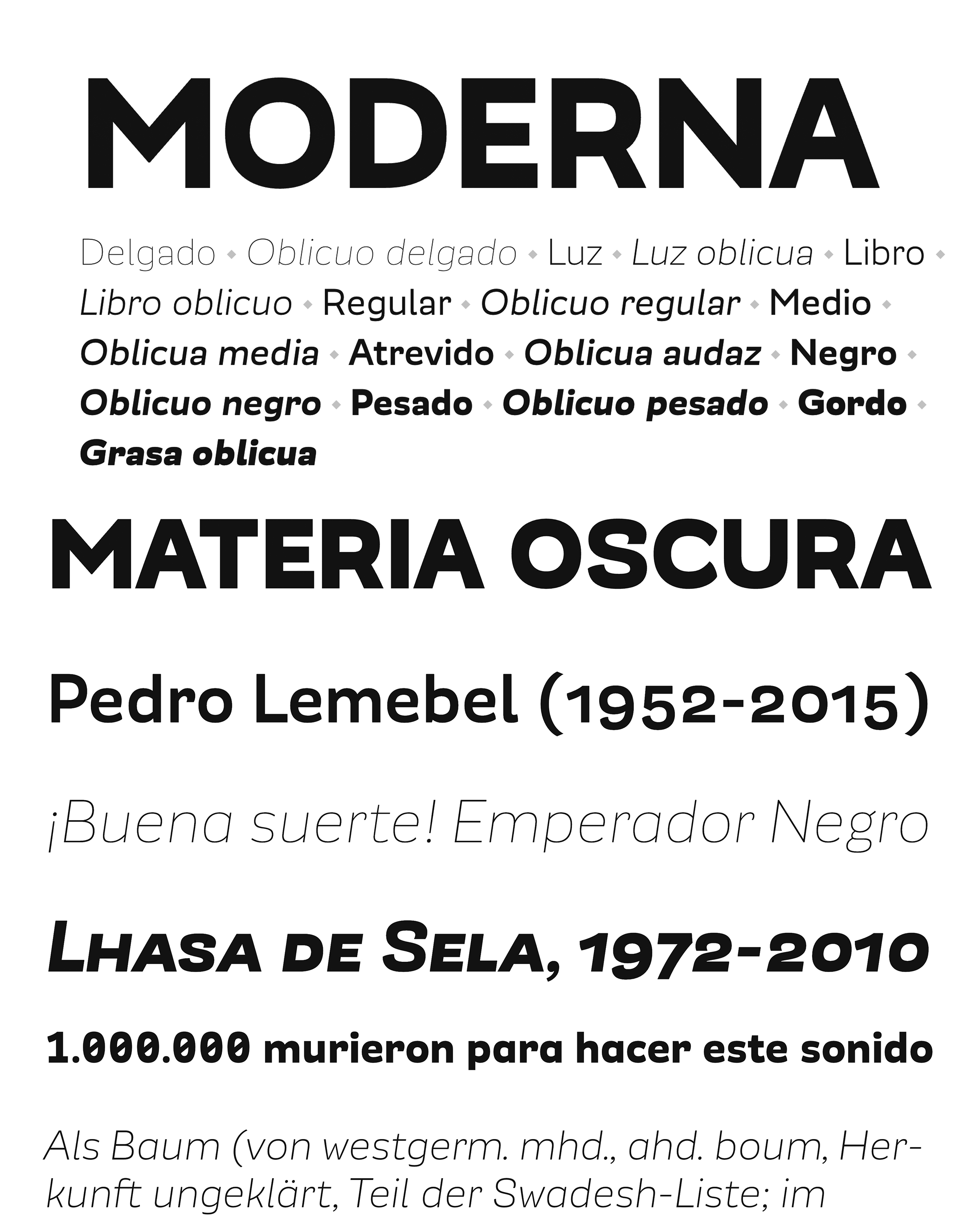
| Año | 2014 — Actualizada: ( 2020 ) |
| Créditos | Guido Ferreira, Javier Quintana |
| Descripción | Modérnica es una tipografía sans serif que incluye estilos romanos y oblicuos en 9 grosores. Su diseño presenta dos características distintivas: un contraste ligeramente invertido y trazos y terminales curvos que evocan sutilmente la forma de las letras sans serif dibujadas con pincel. Publicada originalmente en 2014, en 2020 lanzamos la versión 2.0, en la que ampliamos la cobertura lingüística y el conjunto de caracteres, añadiendo un nuevo grosor Fat, cifras tabulares, fracciones inteligentes y flechas. Hemos mejorado las funciones OpenType con nuevos conjuntos estilísticos. |
| Familia(s) | Delgado, Oblicuo delgado, Luz, Luz oblicua, Libro, Libro oblicuo, Regular, Oblicuo regular, Medio, Oblicua media, Atrevido, Oblicua audaz, Negro, Oblicuo negro, Pesado, Oblicuo pesado, Gordo, Grasa oblicua |
| Fundidora | Quintana fonts |